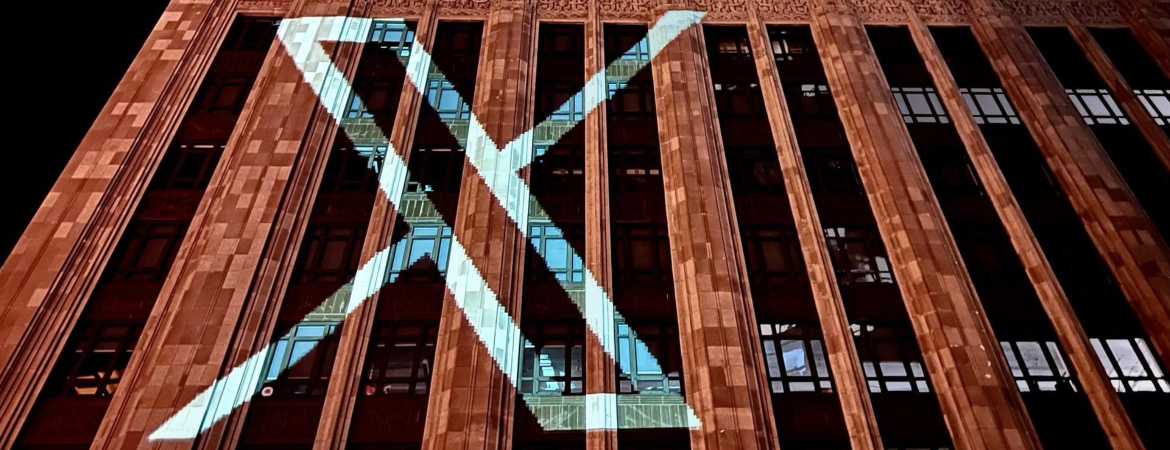
Le vol de l’oiseau bleu s’arrête.
Larry, l’oiseau bleu qui est autant le logo que le symbole de Twitter depuis 2012, ainsi que le nom de l’application (signifiant gazouillis en français), sont voués à disparaître. En effet, la folie de changement d’Elon Musk ne pouvait pas s’arrêter à rendre le symbole de certification payant, ou bien à limiter le nombre de tweets visibles par les utilisateurs ; il lui fallait également réaliser ses lointains rêves de X : un changement qu’il a annoncé lundi 24 juillet.
En effet, Musk semble être fan de la lettre X. En 2001, sa deuxième startup, nommée x.com, a été fusionnée avec son concurrent et malgré ses tentatives pour garder son nom, celui-ci est devenu plus tard PayPal. On peut également penser à SpaceX ou au nom de son fils, X Æ A-12. Avec ce rebranding de Twitter, Elon Musk a une quatrième chance avec la lettre X, de quoi lui permettre de faire ressortir son potentiel complet.
Cependant, X ne représente pas qu’un rebranding de Twitter, mais aussi des changements majeurs apportés à l’application. Celle-ci ne serait plus un simple réseau social, mais accueillerait aussi des fonctionnalités de gestion d’argent ou de jeu vidéo, à la manière de la super app WeChat en Chine. L’ambition ultime d’Elon Musk pour son nouveau joujou chèrement acquis.
Mais cela va-t-il vraiment profiter à Twitter ? En effet, jusqu’ici, le rachat de l’application par l’entrepreneur n’a pas vraiment eu l’air de fournir des résultats concluants : les revenus publicitaires de la plateforme ont chuté de 50 % en 6 mois. Le passage à X va-t-il revitaliser une application qui semble en bout de course ? Ce changement est autrement plus risqué alors que “tweet” et “tweeter” sont devenus respectivement un nom et un verbe couramment usités.
En réaction à cette annonce, Twitter, ou X désormais, a fait ce qu’il fait de mieux : des blagues. Car ce changement semble avoir été opéré à la va vite : si X apparait désormais au lancement de l’application, les stigmates de Twitter perdurent. Sans doute le temps d’habituer les utilisateurs à cette mutation et de ne pas plus les dérouter qu’ils ne le sont déjà.
Certains s’amusent aussi du nouveau logo présenté par Elon Musk… et sa relative simplicité.
Se posent aussi des questions quant à l’origine et la filiation de ce nouveau logo, mais aussi de la typographie dont il est tiré. Celui-ci semble avoir été inspiré (si ce n’est purement et simplement copié) de la police Special alphabets 4 de Monotype, poussant certains internautes à se demander si le boss de Tesla a payé les droits nécessaires pour son utilisation. Sans compter qu’un logo tiré d’une police présente sur internet et non pas créé pour l’occasion, cela fait un peu tâche.
La version la plus proche du logo utilisé par Elon semble avoir d’abord été créée pour un podcast nommé X Pod, dans lequel son créateur discutait de sujets reliés à… Elon Musk. Comme le dit le créateur du podcast, “Le X a été inspiré par Elon, ce doit donc être le destin qu’Elon soit inspiré par le X”.
Autre problème et non des moindres, c’est le groupe Meta (Facebook) qui détient l’usage commercial de X comme réseau social, et Microsoft celui dans le segment finance et e-commerce.
Nous ne sommes pas au bout de nos surprises…